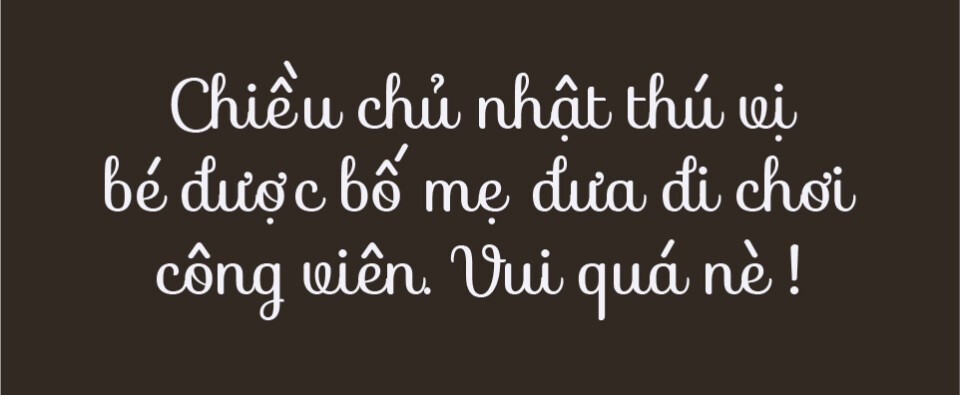
Font VNF là tên gọi đại diện cho kho phông chữ đồ sộ được Việt hóa bởi cộng đồng Vietnam Font (VNF), một trong những nhóm tiên phong mang các tác phẩm Typography quốc tế đỉnh cao về với thị trường đồ họa trong nước. Với sự đa dạng trải dài từ các dòng Sans-serif tối giản, Serif sang trọng cho đến các kiểu chữ viết tay Script bay bổng, hệ thống phông chữ VNF đã trở thành nguồn tài nguyên không thể thiếu cho các dự án nhận diện thương hiệu và thiết kế bao bì chuyên nghiệp. Doozypack.vn chia sẻ link download font VNF Việt hóa trọn bộ chuẩn kỹ thuật, giúp bạn sở hữu kho phông chữ toàn diện mà không lo gặp lỗi nhảy font hay sai lệch dấu câu.
Bộ Font VNF là gì? Tầm ảnh hưởng trong cộng đồng thiết kế Việt Nam
Cùng với các hệ font như SVN hay iCiel, VNF đã đặt nền móng vững chắc cho phong trào chuẩn hóa Typography tiếng Việt, giúp các designer trong nước dễ dàng tiếp cận những xu hướng thiết kế mới nhất trên thế giới.
Di sản từ cộng đồng Việt hóa phông chữ hàng đầu
Đặc trưng lớn nhất của Font VNF là tính chọn lọc cao. Các bộ font được gắn tiền tố VNF hầu hết bắt nguồn từ những xưởng đúc chữ danh tiếng toàn cầu, sở hữu cấu trúc hình học chuẩn xác, tỷ lệ vàng và tính thẩm mỹ vượt trội. Thay vì phải tự vẽ dấu thủ công một cách chắp vá, các nhà thiết kế có thể sử dụng ngay những phông chữ đã được căn chỉnh tỉ mỉ, giúp đẩy nhanh tiến độ hoàn thiện bản vẽ kỹ thuật và ấn phẩm truyền thông.
Tiêu chuẩn xử lý dấu tiếng Việt chuẩn mực và tinh tế
Nỗi sợ lớn nhất của designer khi sử dụng phông chữ ngoại quốc là các dấu thanh tiếng Việt bị quá to, quá nhỏ hoặc đè nét lên thân chữ làm phá vỡ nhịp điệu của thiết kế. Phiên bản font VNF Việt hóa giải quyết triệt để vấn đề này nhờ kỹ thuật tinh chỉnh dấu thủ công. Từng dấu sắc, huyền, hỏi, ngã, nặng được cân đối hài hòa với độ dày nét và độ nghiêng của chữ gốc, bảo đảm văn bản tiếng Việt hiển thị đẹp mắt, chuẩn mực trên mọi ấn phẩm in ấn thực tế.
Các phong cách phông chữ VNF nổi bật nhất hiện nay
- Nhóm VNF Sans-serif hiện đại: Tiêu biểu như VNF Helvetica, VNF Gotham, VNF Din… Cấu trúc chữ không chân sạch sẽ, rõ nét, tối ưu cho việc trình bày bảng thành phần, hướng dẫn sử dụng và thông tin kỹ thuật.
- Nhóm VNF Serif quý phái: Sở hữu chân chữ sắc sảo, độ tương phản nét thanh đậm cao, lý tưởng cho tên các dòng sản phẩm cao cấp, hộp quà tặng doanh nhân hoặc nhãn mác thời trang Luxury.
- Nhóm VNF Script & Brush: Những nét chữ viết tay mềm mại hoặc nét cọ phóng khoáng, thích hợp làm điểm nhấn tiêu đề trên thiệp cảm ơn, bao bì bánh ngọt thủ công hoặc thực phẩm hữu cơ.
- Nhóm VNF Display độc bản: Phong cách hình khối phá cách, dày dặn, giúp tiêu đề chính trên mặt trước hộp giấy hoặc túi giấy thu hút thị giác khách hàng ngay lập tức.
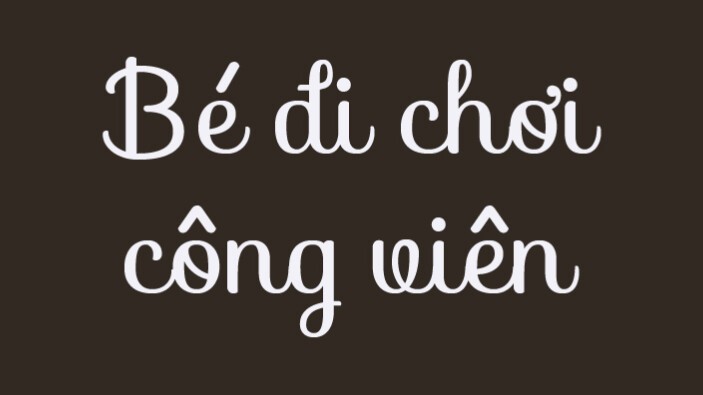
Tại sao designer nên sở hữu bộ font VNF Việt hóa full cho thiết kế bao bì?
- Đồng bộ nhận diện thương hiệu: Thư viện VNF cung cấp đầy đủ các biến thể từ cực mảnh (Thin) đến cực đậm (Black), giúp bạn dễ dàng đồng bộ hình ảnh từ logo, website đến vỏ hộp sản phẩm thực tế.
Lời khuyên từ xưởng in: Đối với các bản thiết kế in ấn bao bì cao cấp tại Doozypack.vn, bạn nên ưu tiên cài đặt định dạng OTF. Bản OTF giúp các đường cong của phông chữ giữ được độ mịn tuyệt đối khi xuất file PDF chất lượng cao, hạn chế tình trạng răng cưa khi phóng lớn tên thương hiệu.
03 Ứng dụng thực tế của font VNF trong sản xuất bao bì tại Doozypack.vn
Sự toàn diện của hệ thống font chữ VNF mang lại hiệu ứng thị giác đắt giá trên các dòng sản phẩm bao bì thực tế do Doozypack.vn sản xuất: